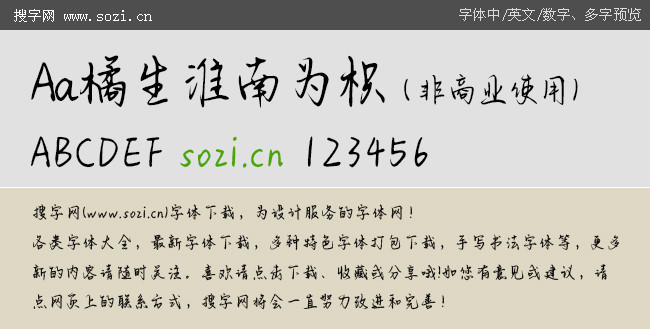
Aa橘生淮南為枳
搜字網(wǎng)給大家提供一款A(yù)a橘生淮南為枳(非商業(yè)使用)字體下載,這款字體是一款極具個(gè)性的手寫藝術(shù)字體,風(fēng)格比一般的字體更有特色,連貫字跡顯得干練而不凌亂,清新簡明,具有很好的視覺感。適合書裝設(shè)計(jì)、包裝設(shè)計(jì)、海報(bào)設(shè)計(jì)等應(yīng)用(此字體為個(gè)人非商用版,商用可以聯(lián)系QQ:1006760504)。